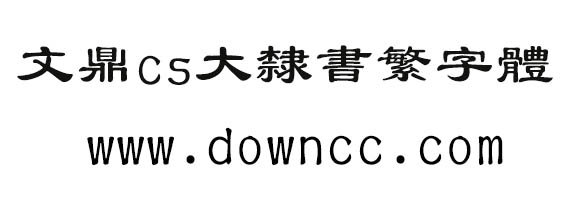
文鼎cs大隸書(shū)繁體是一款設(shè)計(jì)中常用的繁體字體。該字體的結(jié)構(gòu)比較清晰,筆畫(huà)中粗,設(shè)計(jì)師們的最愛(ài)。趕快到綠色資源網(wǎng)下載體驗(yàn)吧!
文鼎cs大隸書(shū)繁體如隸書(shū)一般書(shū)寫(xiě)有力,呈現(xiàn)的是扁平,橫長(zhǎng)豎短,然后結(jié)果繁體就更加的美觀。